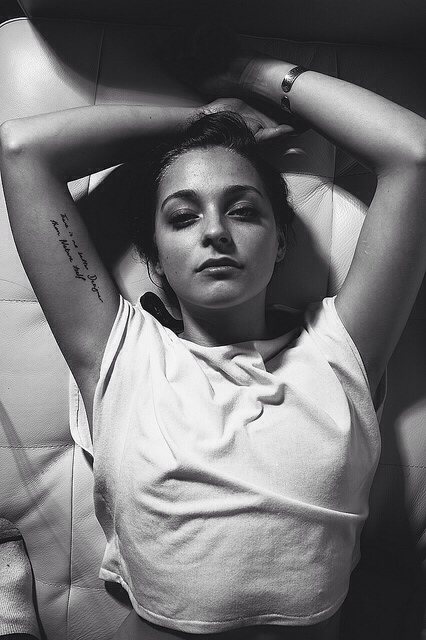
Welche Schriftart + Größe ist das? (Tattoo)
ich lasse mir in 2 Wochen ein Tattoo stechen und wollte jetzt nachfragen, ob jemand weiß, welche Schriftart bei dem unten angehängten Tattoo verwendet wurde und welche Größe in etwa verwendet wurden ist?
im englischen wird der tätowierer (auch) ›tattoo artist‹ genannt, also tattookünstler. das heißt: ein guter tätowierer als künstler aus eigenem recht erstellt seine gestaltungsvorlagen nicht zwangsläufig auf der basis von satzschriftarten (fonts). er kann die vorlage aus der freien hand selbst zeichnen oder, wenn er das nicht kann (oder sein stil dem kunden nicht zusagt), einen kalligrafen – einen schönschreiber, wörtlich übersetzt – damit beauftragen. nur dadurch ist sichergestellt, dass die ideen der kunden individuell umgesetzt werden und das ergebnis nicht aussieht, als hätte h&m jetzt auch tattoos im angebot.
in einer größeren abbildung des tattoos, um das es dir geht, ist zu erkennen, dass der gezeigte schriftzug vermutlich nicht identisch ist mit irgendeiner existierenden schriftart. vergleich mal alle ›r‹, die du siehst. in ›There‹ und ›Nature‹ steht jeweils ein französisches ›r‹, aber beide sehen recht unterschiedlich aus. auch die ›r‹ am ende von ›better‹ und ›Designer‹ ähneln einander kaum. andere buchstaben haben ebenfalls immer unterschiedliche formen, die sich ihren nachbarn anpassen. das geht zwar auch in einem font, aber wird selten so umgesetzt.
mit anderen worten: wenn du ein tattoo willst, das so gut aussieht, dann geh nicht zu jemandem, der bloß so was hier abpausen kann, sondern zu einem künstler, der dir eine individuelle vorlage auf basis deines textwunschs erstellt (oder von einem kalligraphen erstellen lässt). das ist wahrscheinlich wesentlich teurer, als zu hause einen text auszudrucken und sich den 1:1 auf die arschbacke stechen zu lassen – aber hey, du trägst das tattoo die nächsten x jahre mit dir rum, also solltest du dabei zumindest nicht geiziger sein als bei deinem handy oder deinem auto, die (hoffentlich) vor dir selbst schrott sind.
könntet ihr mir aber sagen. welche SChriftrgröße es in etwa ist?
Eine auch nur ungefähre Schriftgröße festzustellen ist ohne Vergleich (Länge Oberarm beispielsweise) ein Ding der Unmöglichkeit. Zumal das keine Satzschrift ist.
Über das Stöckchen
… In einer Tattoo-Diskussion mit Themen anfangen, welche einen gewissen Mindest-IQ voraussetze? …
vom Baume des Vorurteils würde vermutlich nicht mal eines der Ponys aus Deiner Signatur hüpfen wollen.  ;-)
Aber jetzt mal im Ernst: Menschen mit Tätowierungen haben heutzutage in aller Regel nichts mehr mit den Stereotypen aus der vorletzten Jahrhundertwende zu tun. Das bedeutet nicht, dass es heute keine Seeleute oder Sträflinge mit Tätowierungen mehr gibt – aber eben auch nicht den Umkehrschluss: dass alle tätowierten Menschen ausnahmslos Seeleute und Sträflinge wären. Gegen diese Annahme sprechen ja allein schon die nackten Zahlen. In der Arte-Dokumentation »Tattoo total« heißt es dazu …
… dass mittlerweile auch in Deutschland jeder zehnte über 14 Jahren ein Tattoo besitzt. (Quelle)
Kaum vorstellbar, dass in unserem Land so viele Menschen zur See fahren oder einsitzen sollten.  ;-)
Man muss Tätowierungen nicht mögen, aber man kann doch den Menschen, die sich für diese Form des Körperschmuckes entscheiden, einfach mal vorurteilsfrei und freundlich begegnen. Hier in diesem Forum, wo wir uns auf die Fahnen geschrieben haben, die Welt durch gute Gestaltung schöner zu machen, steht es uns gut zu Gesicht, den Tätowierwilligen, die hier Hilfe suchen, ganz entspannt zu einem schön(er)en Ergebnis zu verhelfen. Das schließt den ein- oder anderen Scherz in der Diskussion nicht aus – aber bitte mit den Fragestellern und nicht über sie. Und wer das Thema partout nicht mag, muss ja nicht zwingend an der Diskussion teilnehmen …
Erst wenn dieses dann zu 100% den eigenen Wünschen entspricht, eventuell nach erneutem Einscannen und Ausdruck auf dieser flexiblen Klebefolie, würde ich mich in die Hände des Menschen begeben, der das dauerhaft fest“nagelt“